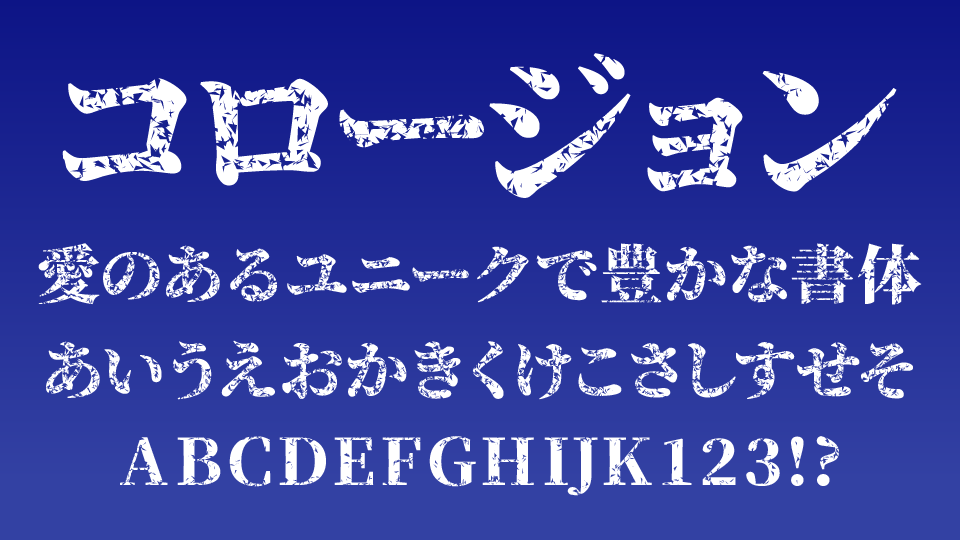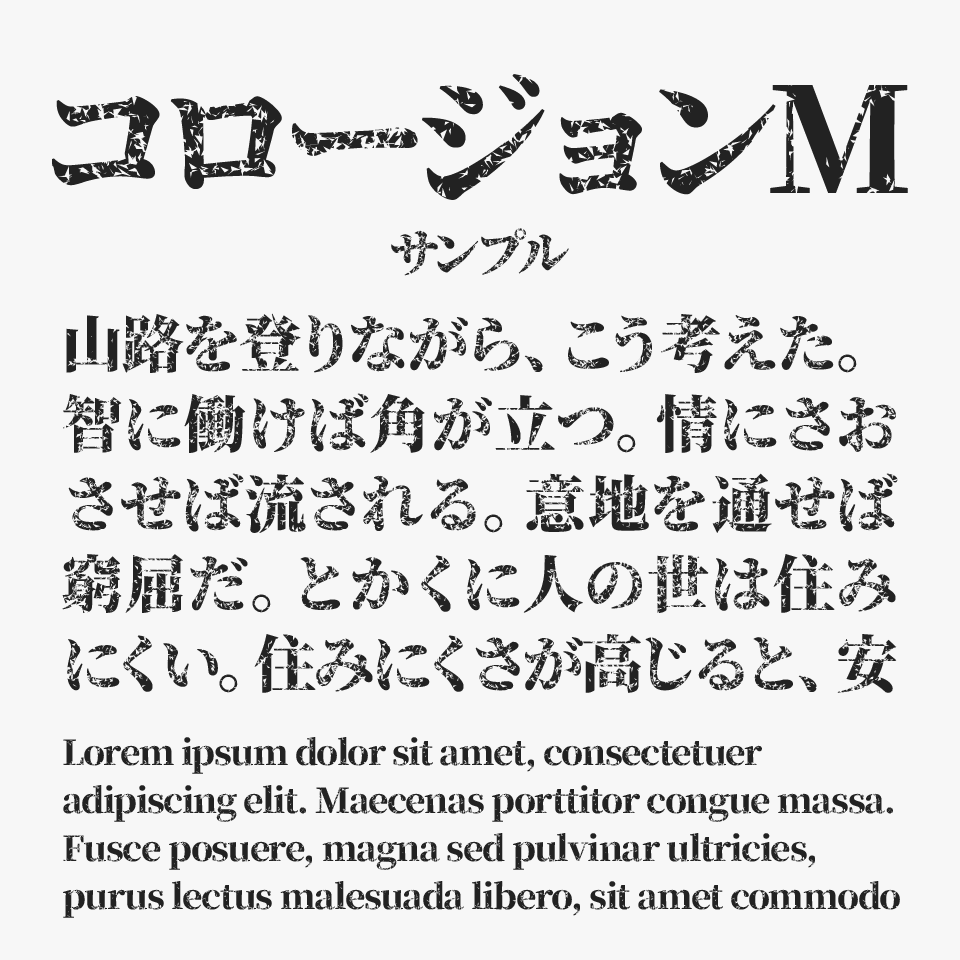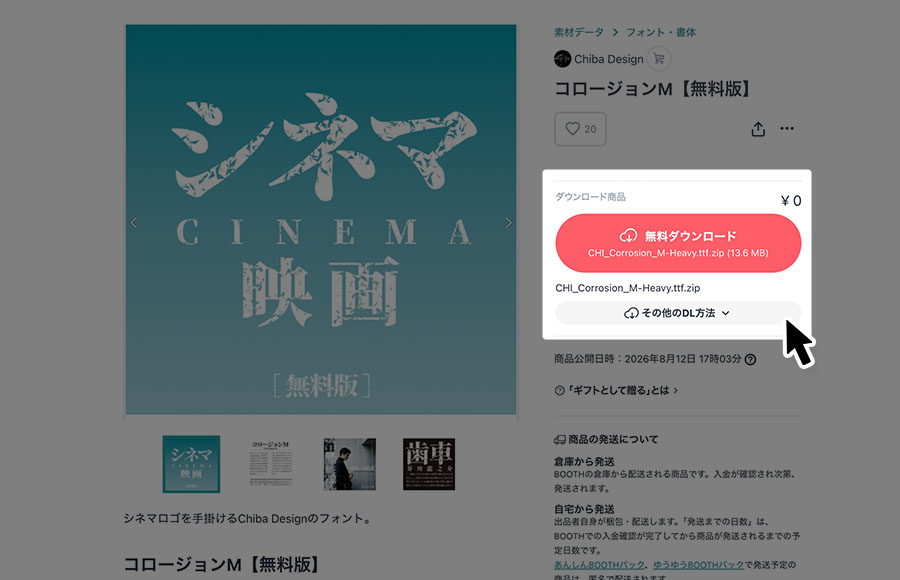
コロージョンM
コロージョンMフォントは、源ノ明朝フォントとベースとして、金属が錆びたり、塗装が剥がれたりしたような質感を文字全体に落とし込んだ、無骨で存在感のあるデザイン明朝体フォントです。
重厚な明朝体をベースにしながら、ランダムに削れた表面や擦れた輪郭によって、長い年月を経たような風合いを表現されたフォントです。ハードな印象がありながらも文字の骨格はしっかりとしているため、タイトルでも高い視認性を保ったまま使うことができます。
ロックやヴィンテージ、ミリタリー、サバイバル、工業デザイン、映画ポスターなど、荒々しく重厚な世界観にぴったりなフォントです。新品ではなく使い込まれたような雰囲気を加えたい場面で、デザイン全体に深みを与えてくれます。